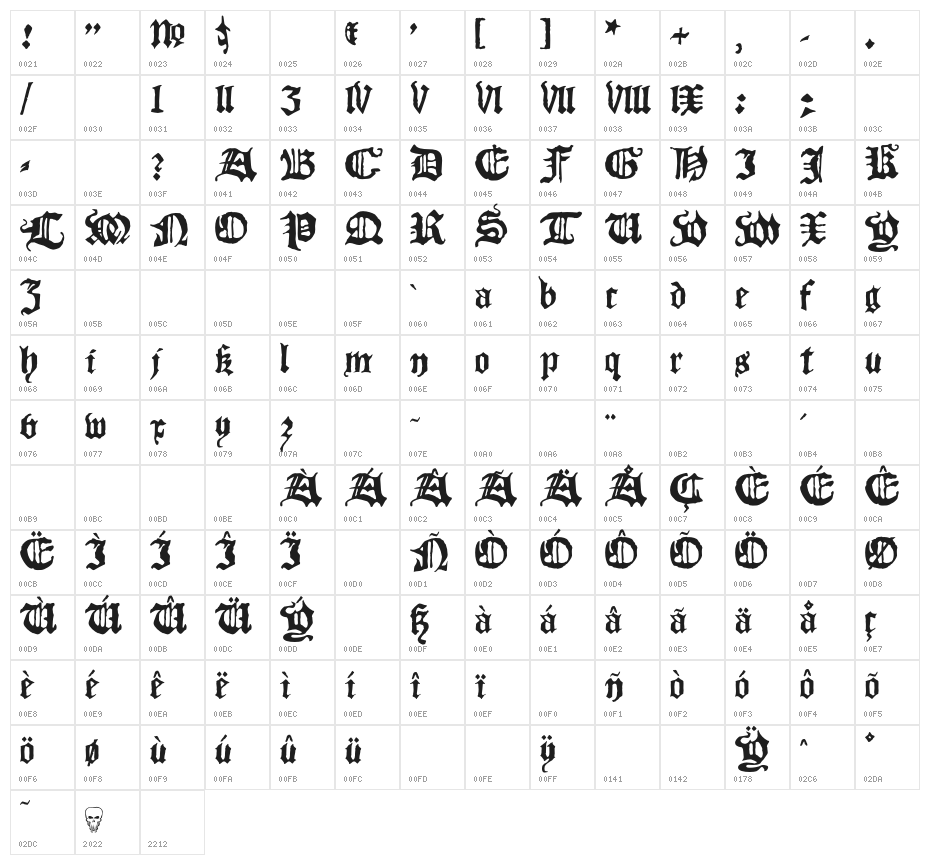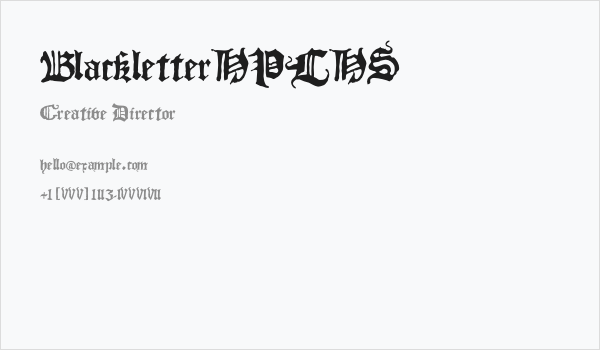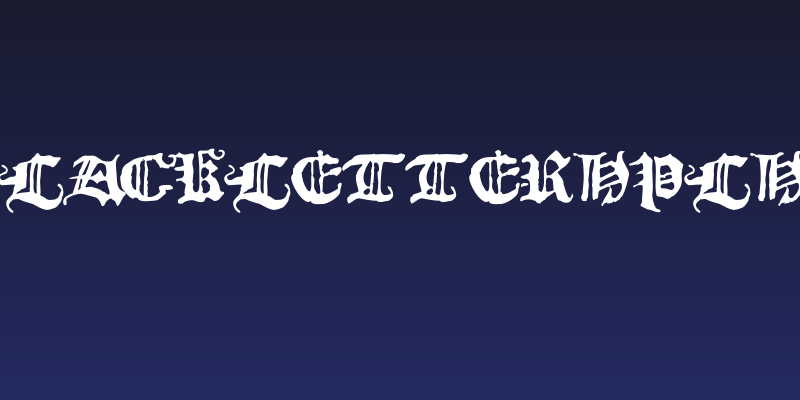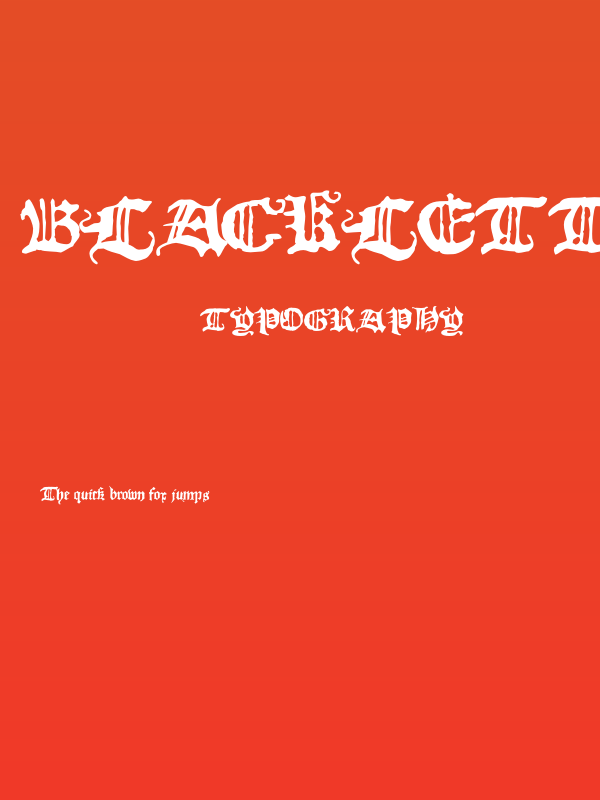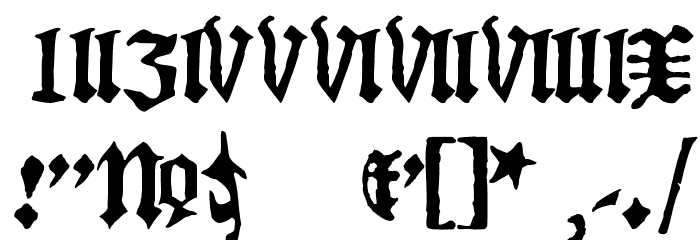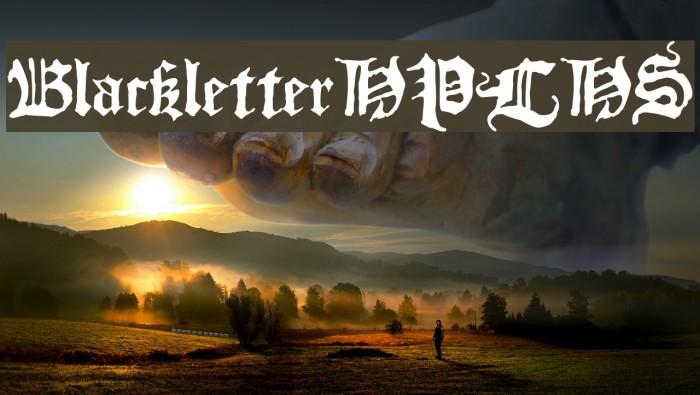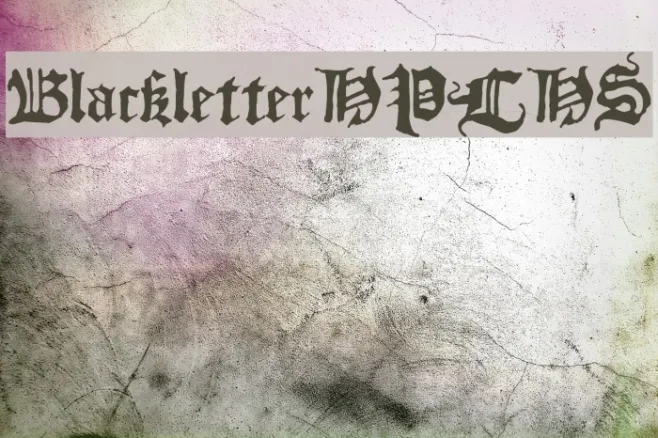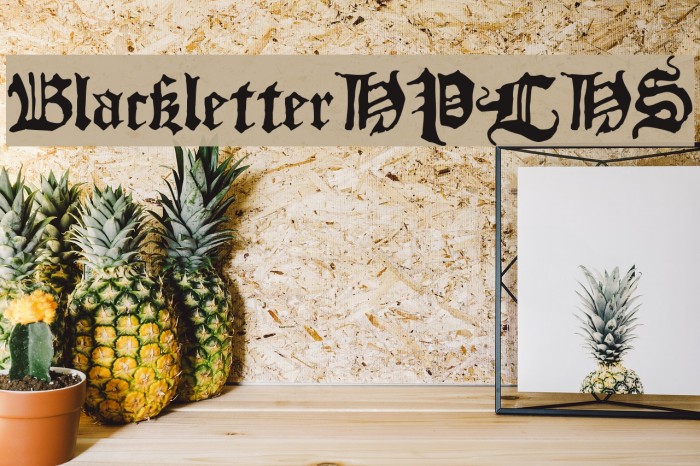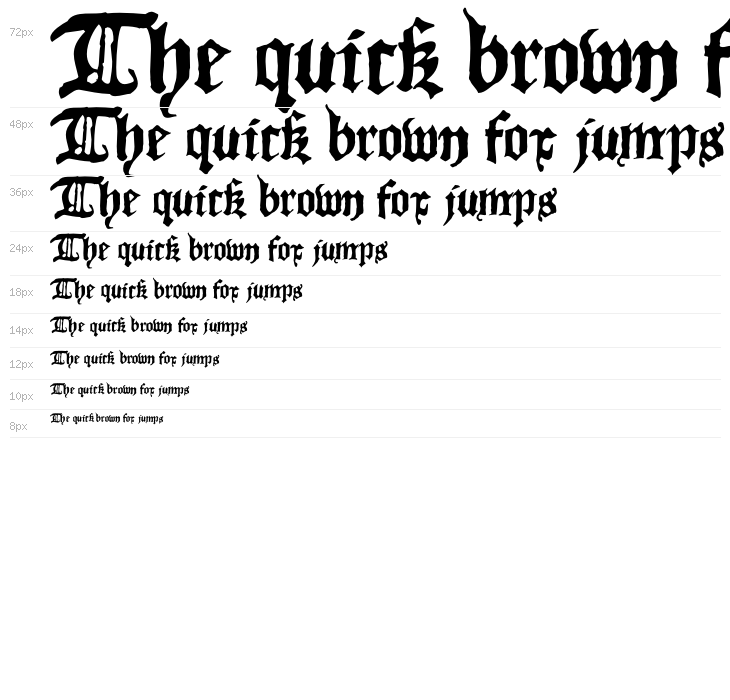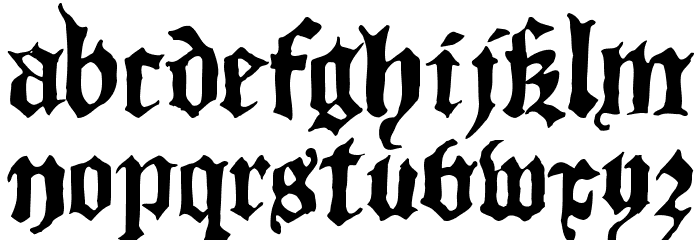
BlackletterHPLHS Font
✎ Gothic
| Caso d'uso | Logos, Headlines, Decorative purposes |
| Progetti proposti | Ideal for historical documents, book covers, posters, and branding that requires a medieval or gothic touch. |